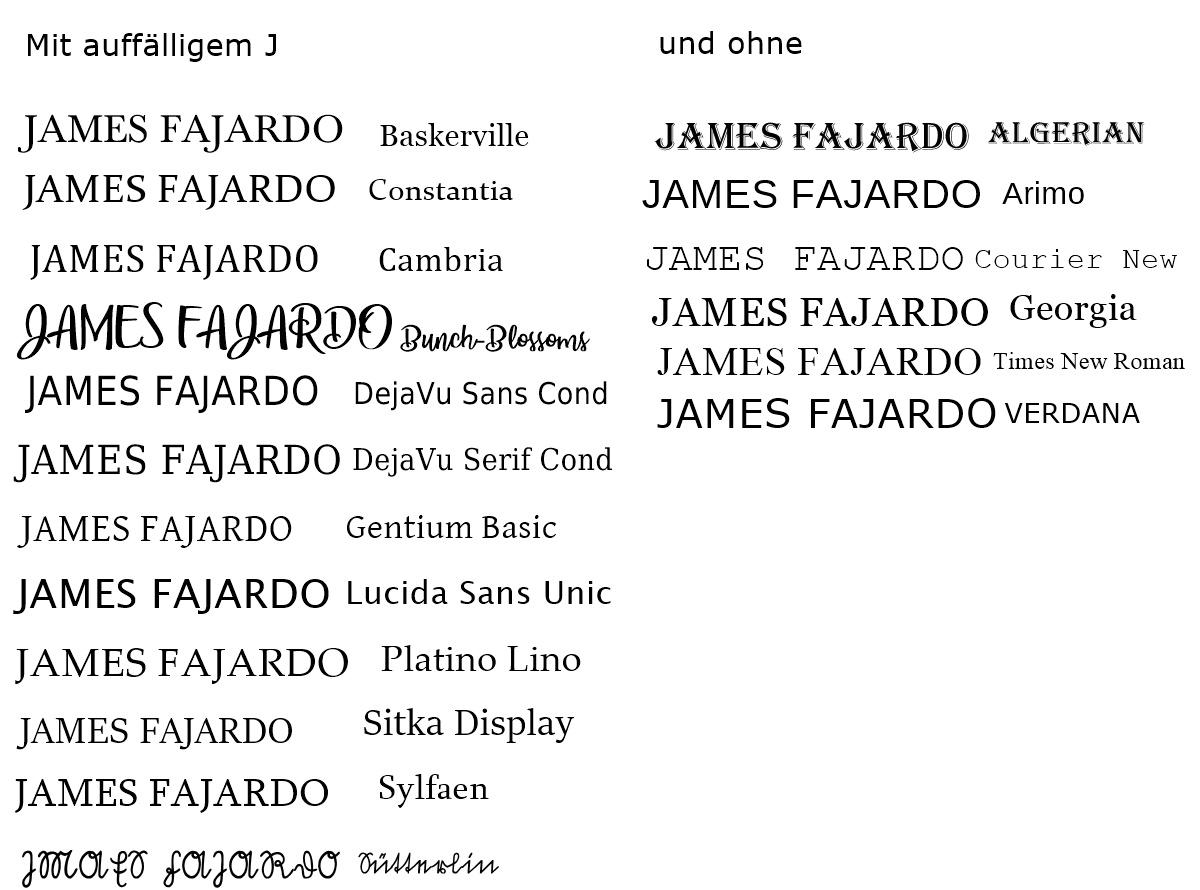
Font mit einem auffälligen J
suche Font mit einem besonders auffälligen J ?
Diese Fonts mit leicht auffälligem J sind auf meinem System installiert:
Silka
Platino Linotype
Sylfaen
SimSun
Kennt Ihr noch mehr?
Vivaldi Italic ….  ist aber sehr subjektiv und bedürfte genauerer Definition was "leicht auffällig" bedeutet. ;-)
Ich habe jetzt einfach mal die Fonts mit einem auffälligen J und ein paar ohne aufgelistet.
Die Fonts sind zwar alle unterschiedlich, bis auf die beiden Handschriften aber auch wiederum nicht.
Deshalb freue ich mich, über eure Vorschläge.